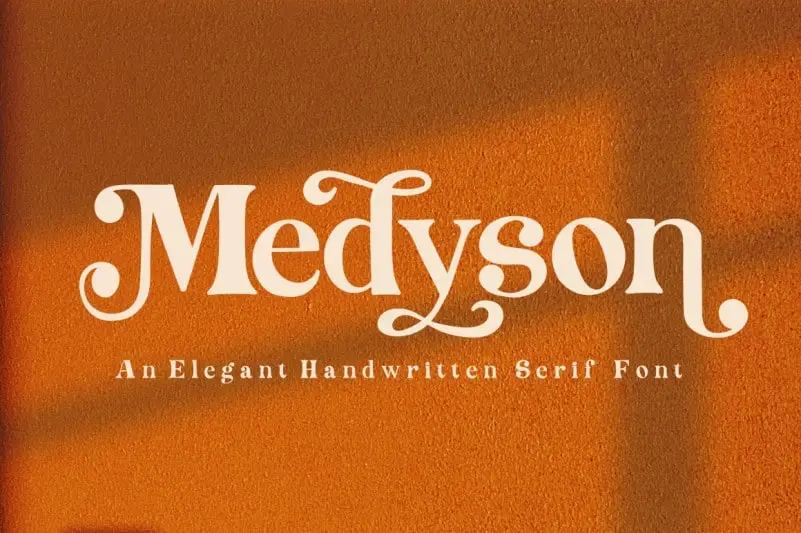
Medyson Serif Font – Download Grátis
Introduzimos a elegante nova Medyson Serif Font. Esta é uma nova fonte serif escrita à mão com toneladas de caracteres alternativos e ligaturas únicas. Ideal para designers que buscam um equilíbrio entre clareza e sofisticação, a Medyson Serif oferece o conforto da tipografia serif combinado com a personalidade única dos caracteres escritos à mão. Essa fonte traz além de sua estética simples e elegante uma variedade impressionante de alternativas de caracteres e ligaturas distintas que proporcionam um toque especial, tornando-a perfeita para aplicações onde a elegância e sofisticação são essenciais. Seja em design gráfico ou editoração de textos, a Medyson Serif é uma escolha segura para qualquer projeto que deseje transmitir ao público uma mensagem clara e envolvente. Ela não apenas respeita as características já apresentadas na descrição original, mas também oferece um toque distintivo que a torna um recurso gráfico indispensável.